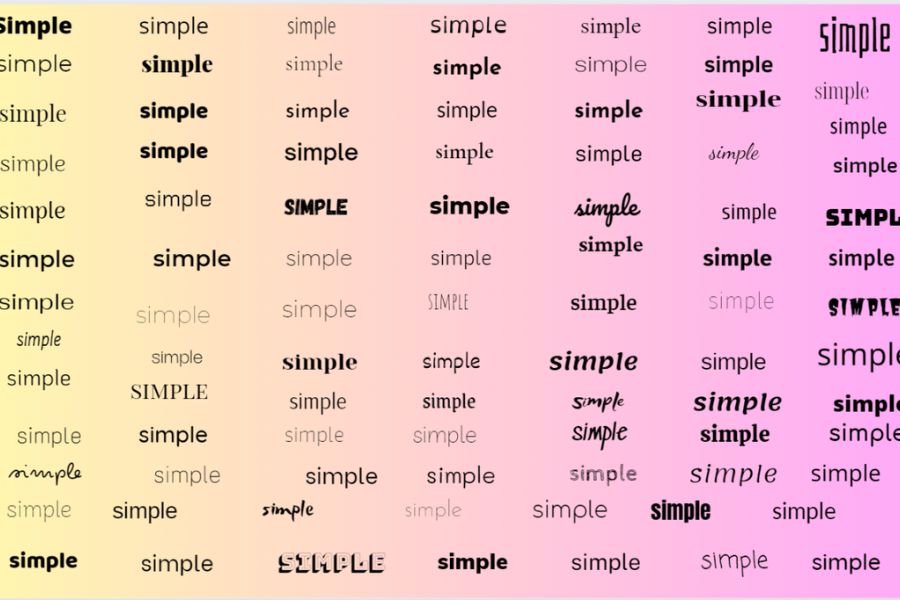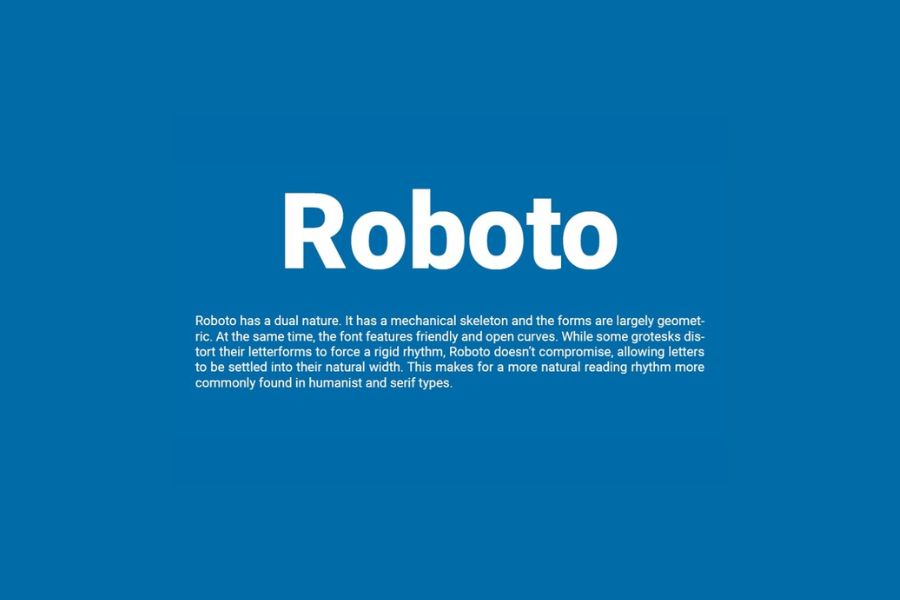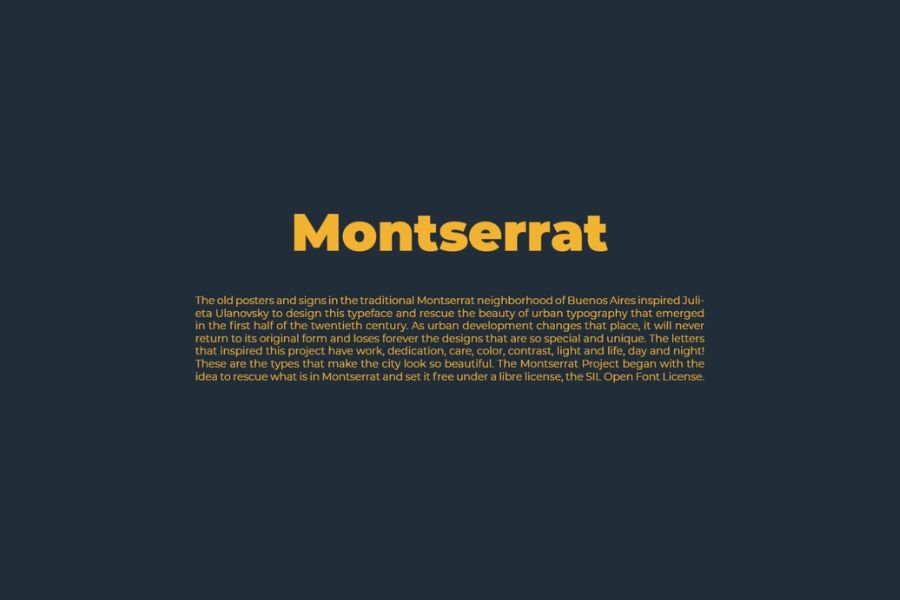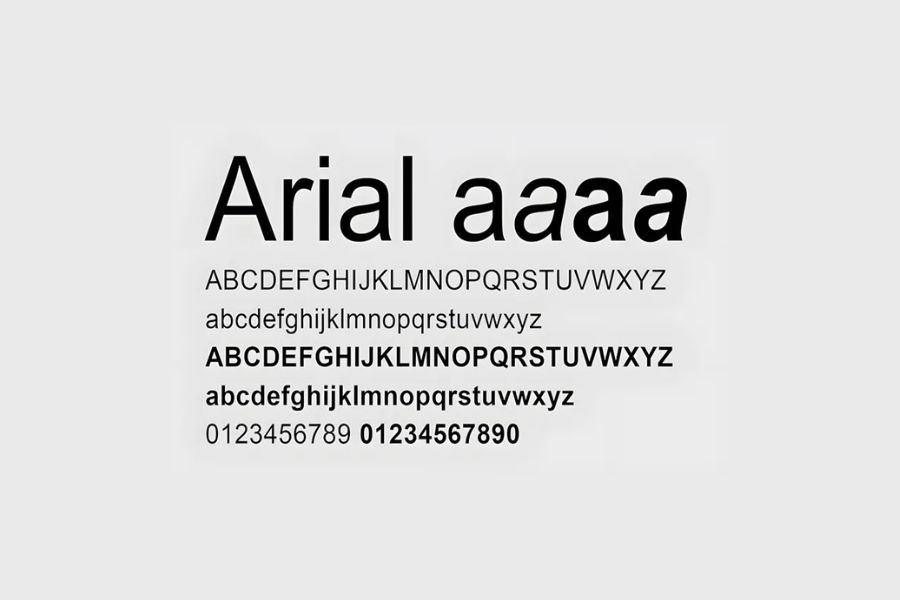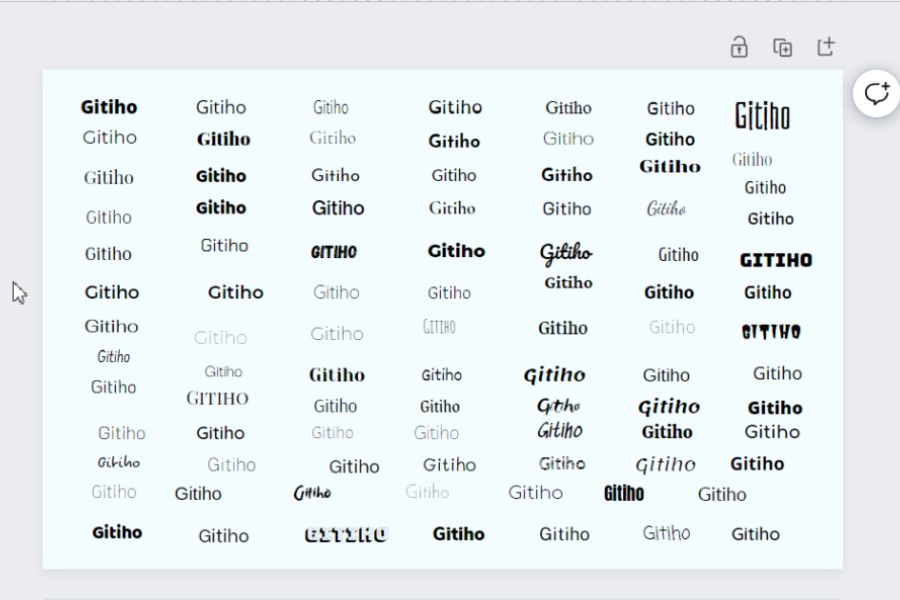
Font Chữ Tiếng Việt Canva: Mẹo Tối Ưu Thiết Kế Đẹp Chuyên Nghiệp, Không Còn Lỗi Font
Canva hiện nay là một trong những công cụ thiết kế đồ họa trực tuyến phổ biến nhất, được hàng triệu người dùng trên toàn thế giới yêu thích. Tuy nhiên, với người dùng Việt Nam, việc lựa chọn font chữ tiếng Việt sao cho đẹp và chuyên nghiệp vẫn là một thử thách lớn. Sử dụng font không phù hợp có thể khiến thiết kế trở nên kém thu hút hoặc gặp lỗi hiển thị. Trong bài viết này, Sadesign sẽ chia sẻ những font chữ tiếng Việt tốt nhất trên Canva, hướng dẫn cách sử dụng chúng hiệu quả cùng các mẹo tối ưu để mỗi sản phẩm thiết kế của bạn trở nên chuyên nghiệp và bắt mắt hơn.
1. Tầm quan trọng của font chữ tiếng việt trong thiết kế
Font chữ không chỉ là yếu tố trang trí hay thẩm mỹ mà còn đóng vai trò quan trọng trong việc truyền tải thông điệp một cách rõ ràng và hiệu quả đến người xem. Với thiết kế dành cho người Việt, việc lựa chọn font chữ hỗ trợ đầy đủ các ký tự tiếng Việt không chỉ giúp nội dung trở nên dễ đọc mà còn tạo ra sự nhất quán và chuyên nghiệp trong tổng thể thiết kế. Một font chữ được chọn kỹ lưỡng sẽ giúp người xem nhanh chóng tiếp nhận thông tin, đồng thời nâng cao giá trị cảm xúc và trải nghiệm thẩm mỹ của sản phẩm.
Bên cạnh yếu tố thẩm mỹ, việc sử dụng đúng font chữ tiếng Việt còn giúp ngăn ngừa các vấn đề kỹ thuật thường gặp khi xuất file, tải lên các nền tảng khác nhau hay in ấn. Một font chữ phù hợp sẽ đảm bảo rằng tất cả các ký tự tiếng Việt, từ cơ bản đến phức tạp, đều hiển thị chính xác và đẹp mắt trên mọi thiết bị. Một số lợi ích rõ ràng khi lựa chọn font chữ tiếng Việt chuẩn bao gồm:
• Giúp người đọc dễ dàng tiếp nhận thông tin và hiểu đúng ý nghĩa của nội dung mà thiết kế muốn truyền tải
• Tạo sự thẩm mỹ và cảm giác chuyên nghiệp, nâng tầm giá trị sản phẩm trong mắt khách hàng hoặc người xem
• Ngăn ngừa các lỗi hiển thị như mất dấu, sai dấu hoặc ký tự không mong muốn khi xuất file hoặc chuyển đổi nền tảng
2. Những lỗi thường gặp khi sử dụng font chữ không hỗ trợ tiếng việt
Khi sử dụng font chữ không hỗ trợ đầy đủ tiếng Việt, nhiều người thiết kế sẽ gặp phải các vấn đề làm giảm chất lượng tổng thể của sản phẩm. Những lỗi này không chỉ ảnh hưởng đến thẩm mỹ mà còn khiến thông điệp bị hiểu sai hoặc khó đọc, từ đó làm giảm trải nghiệm người dùng và sự chuyên nghiệp của thiết kế. Hiểu rõ các lỗi thường gặp sẽ giúp người thiết kế chủ động lựa chọn và tối ưu font chữ một cách hiệu quả, đồng thời tránh những sai sót không đáng có.
Những lỗi phổ biến khi font chữ không hỗ trợ tiếng Việt bao gồm:
• Mất dấu hoặc sai dấu: Các ký tự có dấu như â, ê, ơ, ư, ă thường không hiển thị đúng, khiến nội dung trở nên khó đọc hoặc sai ý nghĩa
• Hiển thị ký tự lạ: Một số font tự động thay thế ký tự tiếng Việt bằng các ký tự không mong muốn, tạo ra sự lộn xộn trong thiết kế
• Đứt nét hoặc mất nét chữ: Khi thay đổi kích thước hoặc sử dụng font chữ ở kích thước nhỏ, các ký tự có thể bị vỡ hoặc không đều, làm giảm tính chuyên nghiệp và thẩm mỹ
Nhận diện được những lỗi này sẽ giúp bạn chọn lựa font chữ phù hợp trên Canva, đồng thời tối ưu hóa thiết kế để vừa đẹp mắt vừa đảm bảo trải nghiệm người xem hoàn hảo.
3. Các Font chữ tiếng Việt phổ biến trên Canva
3.1 Roboto
Roboto là một trong những font chữ phổ biến nhất trên Canva nhờ sự kết hợp hài hòa giữa phong cách hiện đại và tính dễ đọc. Với các nét chữ rõ ràng, cân đối, Roboto mang đến cảm giác chuyên nghiệp nhưng vẫn gần gũi, phù hợp với nhiều loại thiết kế khác nhau từ bài đăng trên mạng xã hội, áp phích quảng cáo đến các tài liệu doanh nghiệp. Font này hỗ trợ đầy đủ ký tự tiếng Việt, vì vậy bạn không còn phải lo lắng về các lỗi mất dấu hay sai ký tự khi sáng tạo nội dung.
Roboto đặc biệt phù hợp cho những dự án yêu cầu sự rõ ràng và dễ tiếp nhận thông tin, ví dụ như các bản trình chiếu, infographic hay banner giới thiệu sản phẩm. Nhờ sự linh hoạt, font Roboto giúp thiết kế vừa hiện đại vừa đảm bảo tính thẩm mỹ, khiến người xem dễ dàng tập trung vào nội dung chính mà không bị rối mắt.
3.2 Lato
Font Lato mang phong cách mềm mại và tinh tế, tạo cảm giác nhẹ nhàng cho các sản phẩm thiết kế. Những đường cong uyển chuyển và cấu trúc chữ cân đối giúp font này vừa dễ đọc vừa mang tính nghệ thuật, thích hợp cho các dự án như poster, thiệp mời hay banner quảng cáo mang phong cách sáng tạo. Lato cũng hỗ trợ đầy đủ các ký tự tiếng Việt, giúp bạn hoàn toàn yên tâm khi sử dụng mà không gặp lỗi hiển thị.